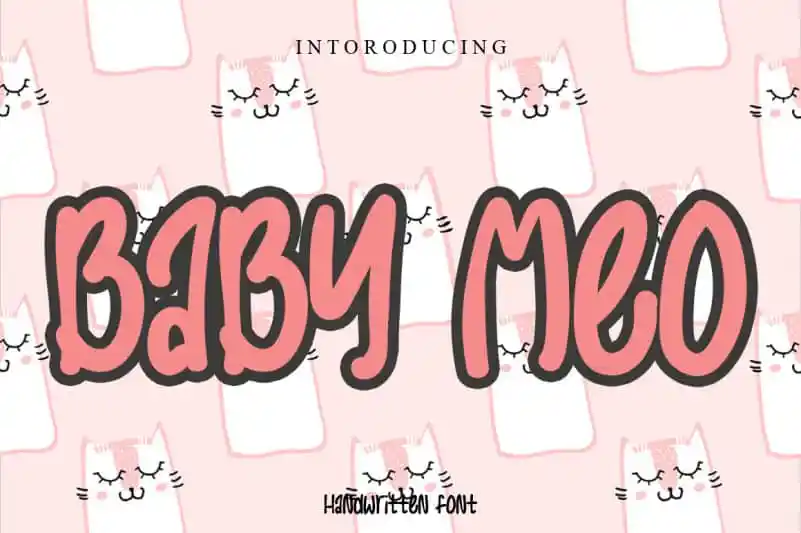
Baby Meo Display Font – Download Grátis
A Baby Meo Display Font é uma seleção única para qualquer projeto visual que valoriza estilo e frescura. Desenvolvida por levincreative, essa fonte é uma mistura relaxante e descontraída de escrita à mão. Seu charme natural e único a tornam perfeita para diversos estilos, desde gráficos divertidos até trabalhos profissionais modernos. Com a Baby Meo Display Font, explorar as inúmeras variações desta fonte é uma experiência de pura diversão visual. Experimente-a no seu próximo projeto e descubra o poder da personalização única que essa font oferece.